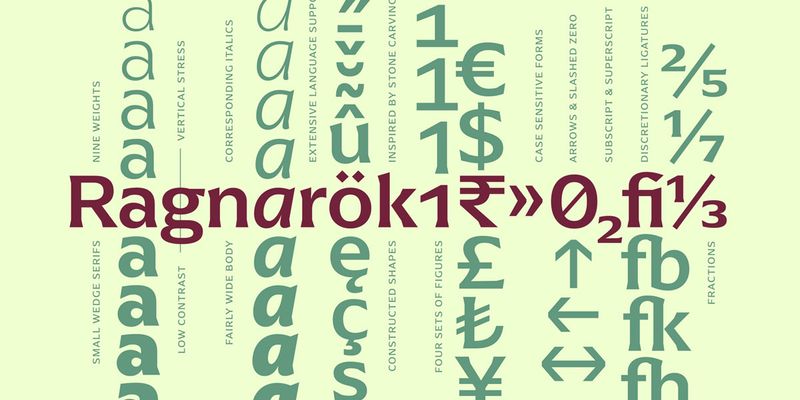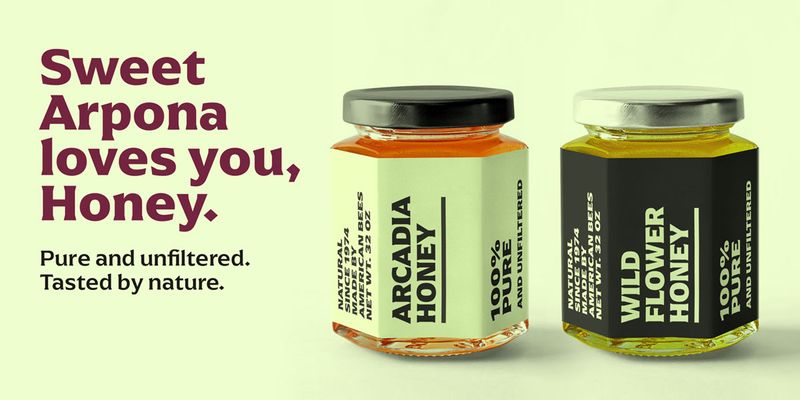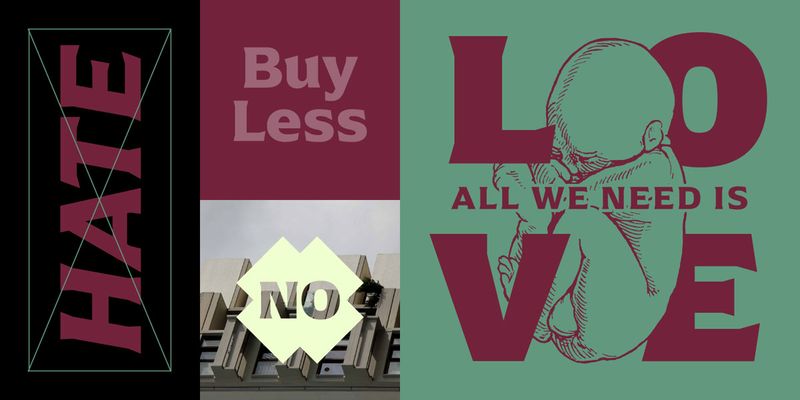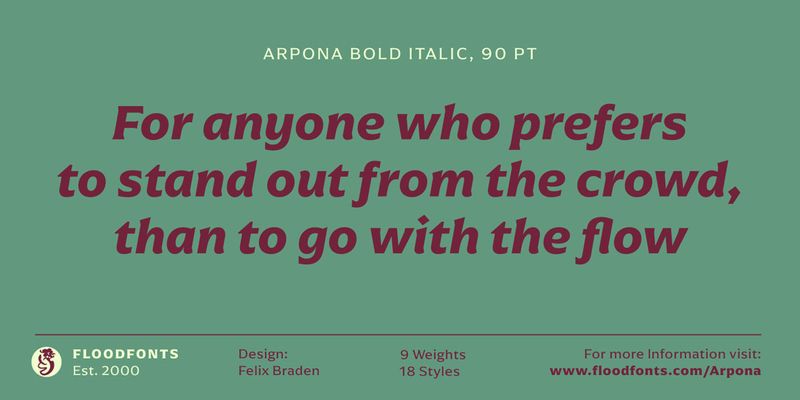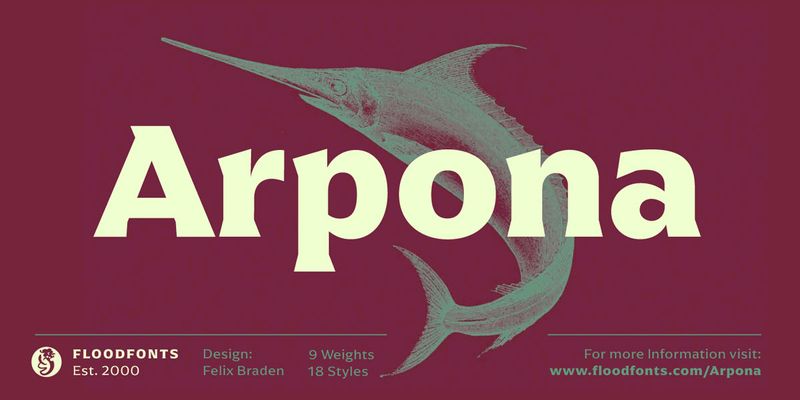
Arpona è un carattere tipografico con piccole grazie a cuneo e un carattere forte, ideale per il design aziendale e tutti i progetti caratterizzati da un senso di individualismo, come arte, moda, cibo, bevande e lifestyle. Grazie alle sue qualità di visualizzazione, Arpona è una buona scelta per il packaging, la pubblicità e il design editoriale ed è ben leggibile anche nell’esecuzione di testo sullo schermo.